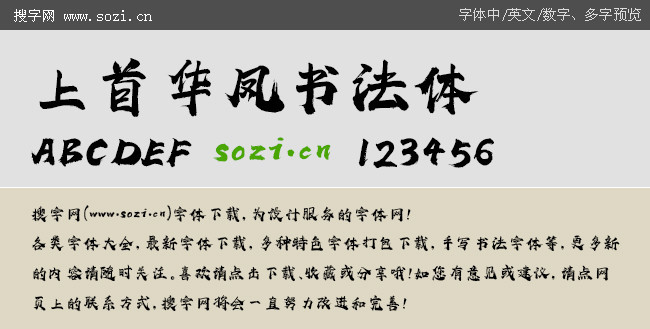
上首華鳳書法體
搜字網(wǎng)給大家提供一款上首華鳳書法體中文字體下載,上首華風(fēng)書法體,字體風(fēng)格穩(wěn)重呈方塊形,字體筆畫豎折處細(xì)節(jié)處理,是此套字庫的亮點。字庫整體特征堅硬、有力,具有現(xiàn)代、國際化的指向性,適用于搭配標(biāo)志、廣告標(biāo)語、商業(yè)廣告等高端屬性。